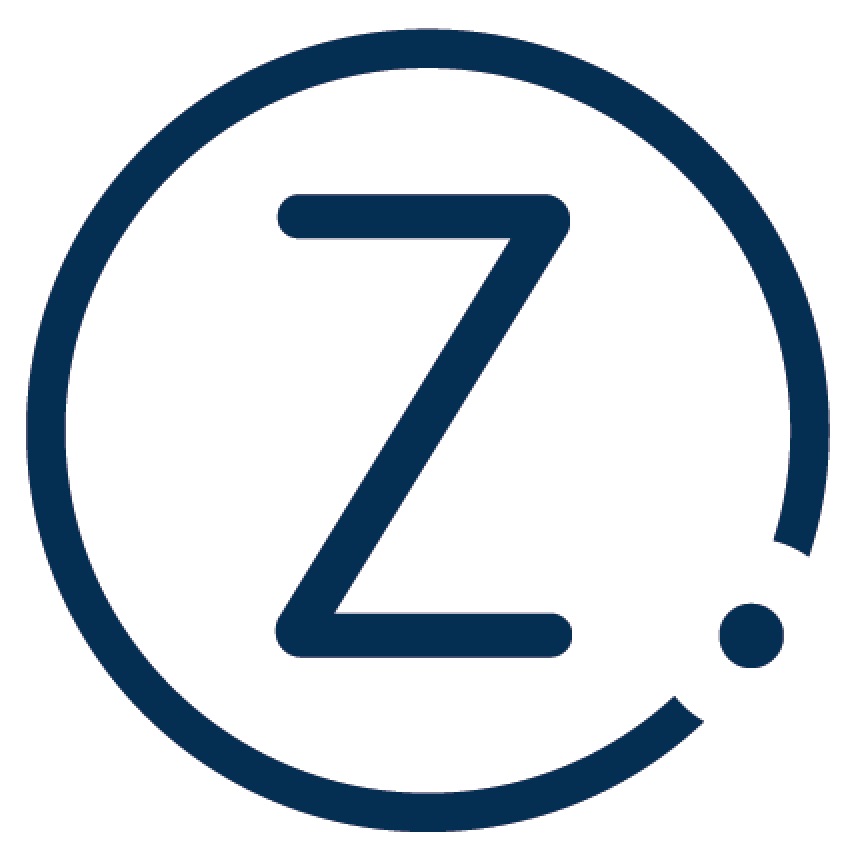
Logos von Start-ups
Bei der Entwicklung von Startup Signets muss es schnell gehen.
Die Logos vieler Start-ups sind Wortmarken. Kein Wunder, das Business ist hart, es geht um Geschwindigkeit, und viele frisch gegründete Unternehmen wissen nicht, ob sie in ein paar Monaten schon wieder vom Markt verschwunden sind. Markenbildung steht da oft hinten an, es muss schnell ein Signet her. Die folgenden Beispiele beweisen, dass es durchaus Logos gibt, hinter denen ein Konzept steckt.
Short Version, Long Version
Das 2015 gegründete Start-up Zeitgold aus Berlin befreit kleine Firmen von Papierkram. Mithilfe einer App lassen sich Buchhaltung, Lohnabrechnung et cetera mit einem Klick am Smartphone erledigen. Hinsichtlich des Logos gab es anfangs einige Versuche mit Bildern, allerdings fanden Zeitgold- Gründer Stefan Jeschonnek und der Designer Mathias Mortag von strandrover.agency die typografische Lösung mit der FF Netto Offc von Daniel Utz schließlich klarer und schneller erfassbar. Gibt es genug Platz, kommt der ausgeschriebene Schriftzug zum Einsatz, steht wie bei einem App-Icon nur eine kleine Fläche zur Verfügung, nutzt Zeitgold das Z im Kreis (oben).
Strukturierend
Die E-Commerce-Plattform für Herren- und Damenwäsche onmyskin 2 wollte ein emotionaler Brand werden. Zeichen & Wunder entwickelte daher unter anderem ein neues Logo. »Im Fashionbereich sind die Kunden Wortmarken gewohnt. Eine zusätzliche Bildmarke war für onmyskin nicht nötig, da der Name schon komplex genug ist«, erklärt Annika Kaltenthaler, Kreativdirekorin bei der Münchner Designagentur. In einem Wort geschrieben ist onmyskin eine Lesefalle, durch die Kombination des handgeschriebenem »my« mit der Sans Serif Halis von Ahmet Altun – die an die Nivea-Type erinnert – ist der Markenname gut erkennbar unddeutlich emotionaler.
Frisch kombiniert
Anfang 2016 ging Offerista aus der Fusion der auf lokales Marketing und Mobile Shopping spezialisierten Firmen barcoo und Marktjagd hervor und sollte nun als Dachmarke in der Kommunikation mit B2B-Kunden etabliert werden. Eine typografische Lösung, die den Namen in den Mittelpunkt rückt, war daher die beste Lösung. Inhouse-Designer René Ahlig visualisierte die zur Marke assoziierten Wörter. So kam es zum Symbol des Markers (zielgerichtet), zu den serifenlosen Schriften Constance von Benoît Sjöholm und Clear Sans von Neil Summerour in Kombination mit warmen und kühlen Farben (persönlich, leidenschaftlich und emotional einerseits, smart und modern andererseits).